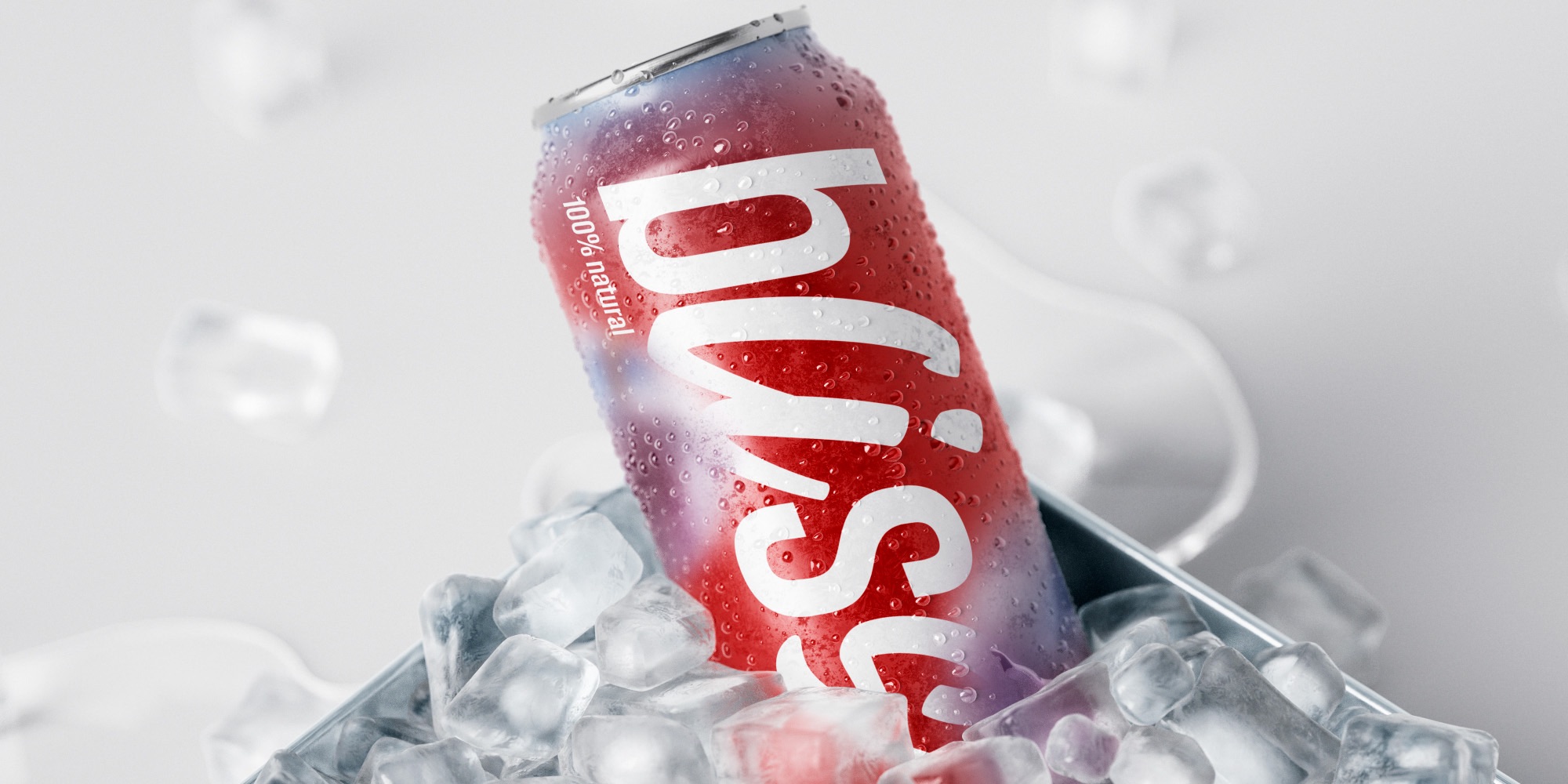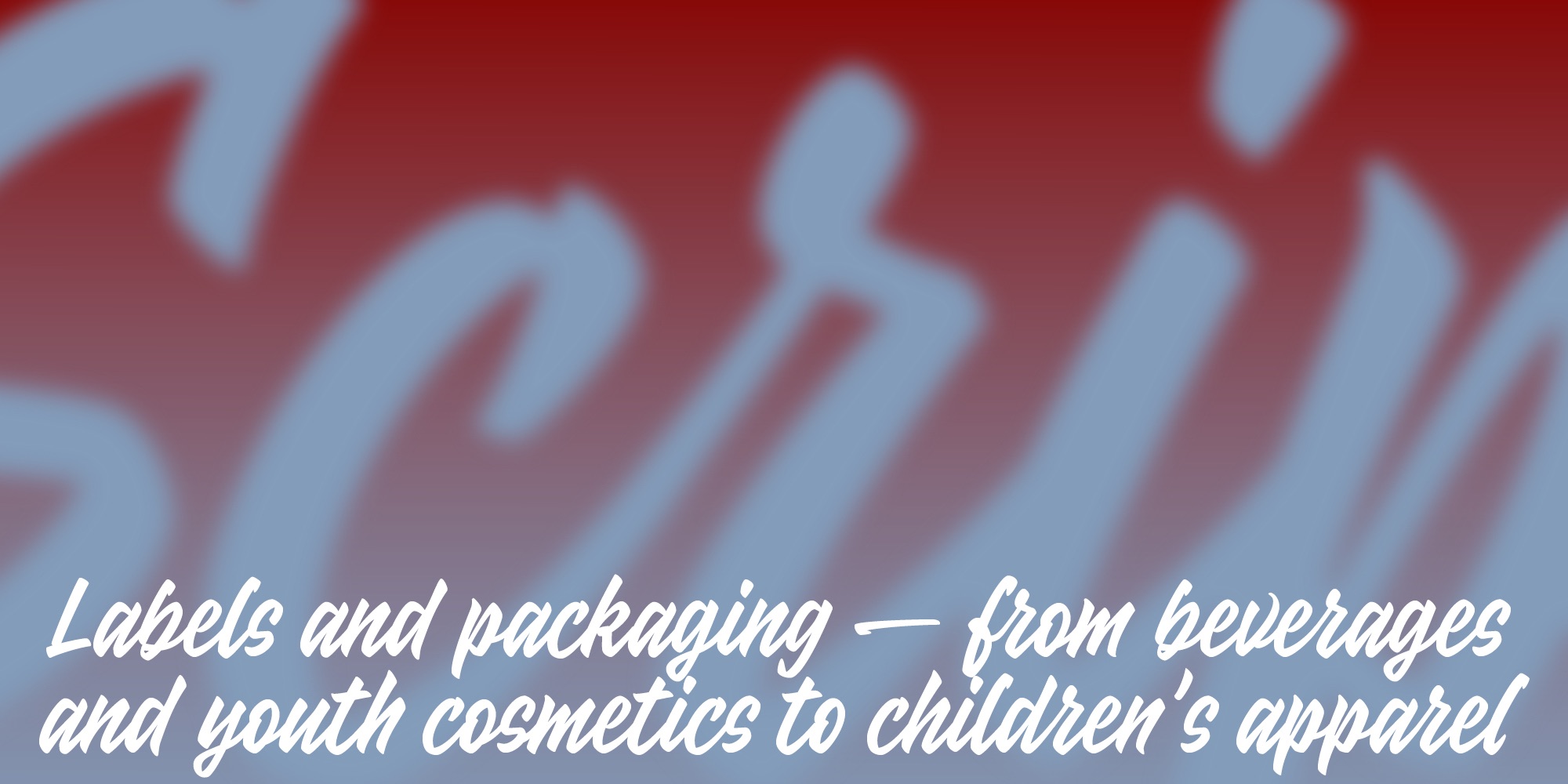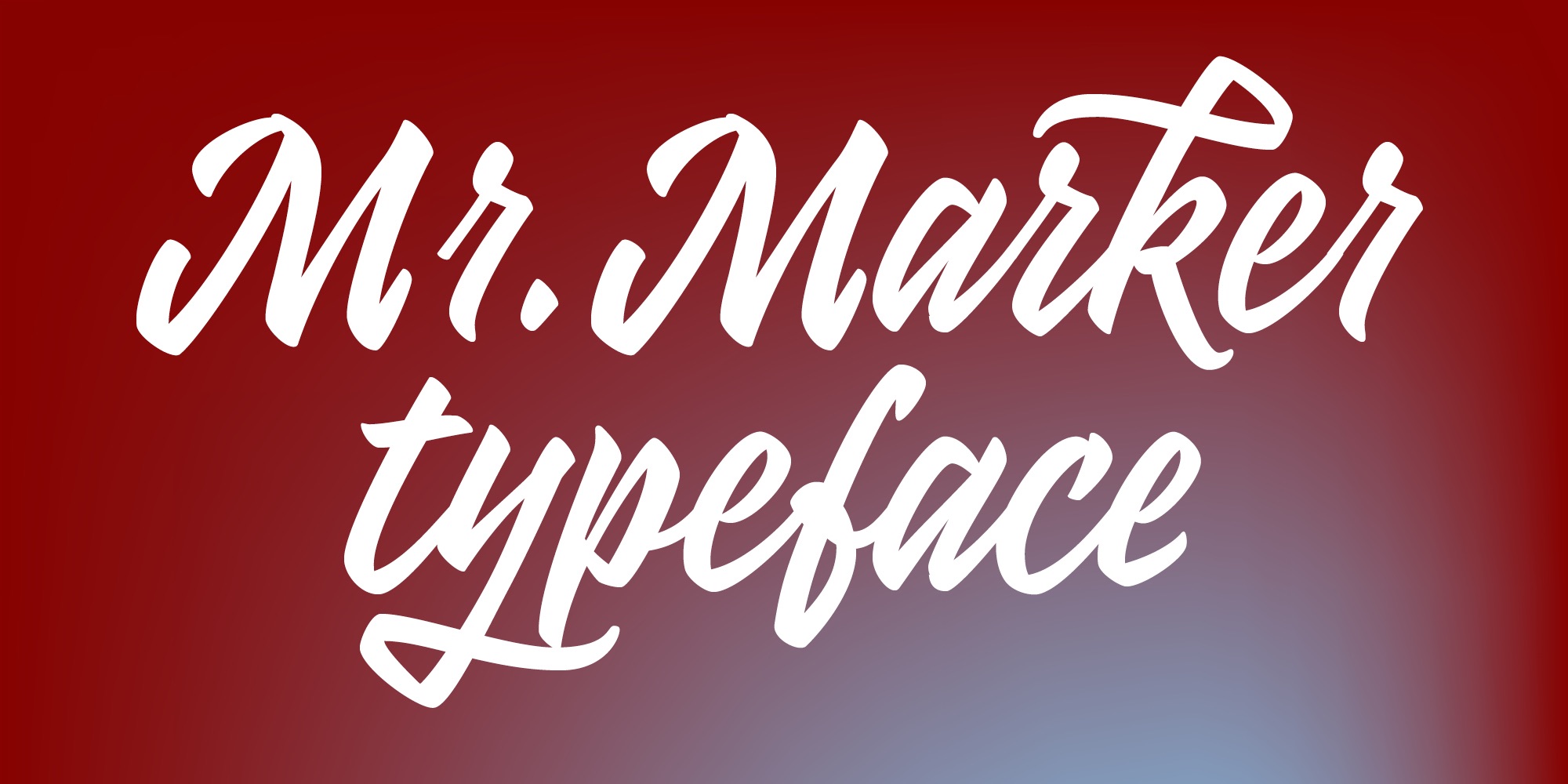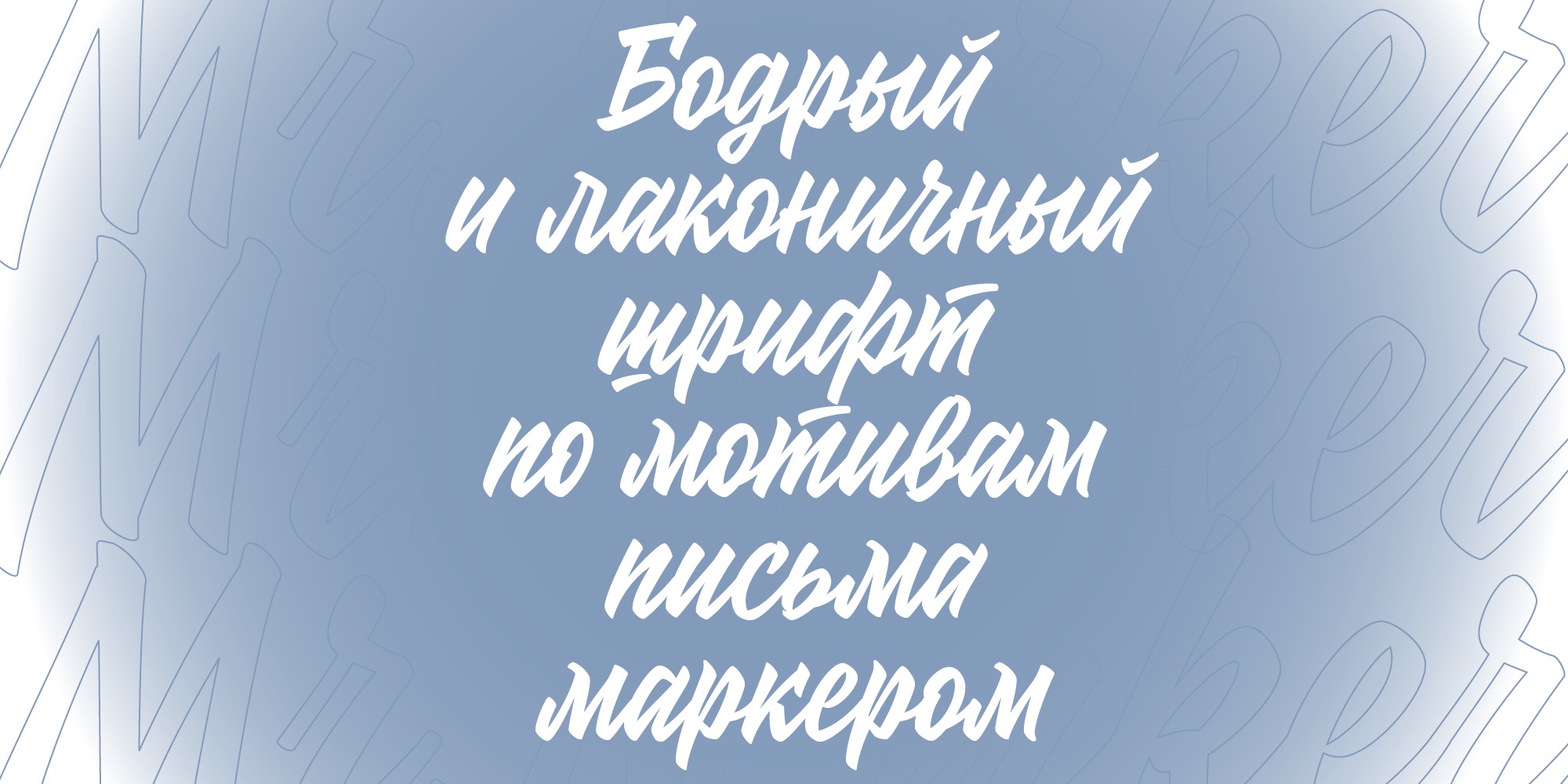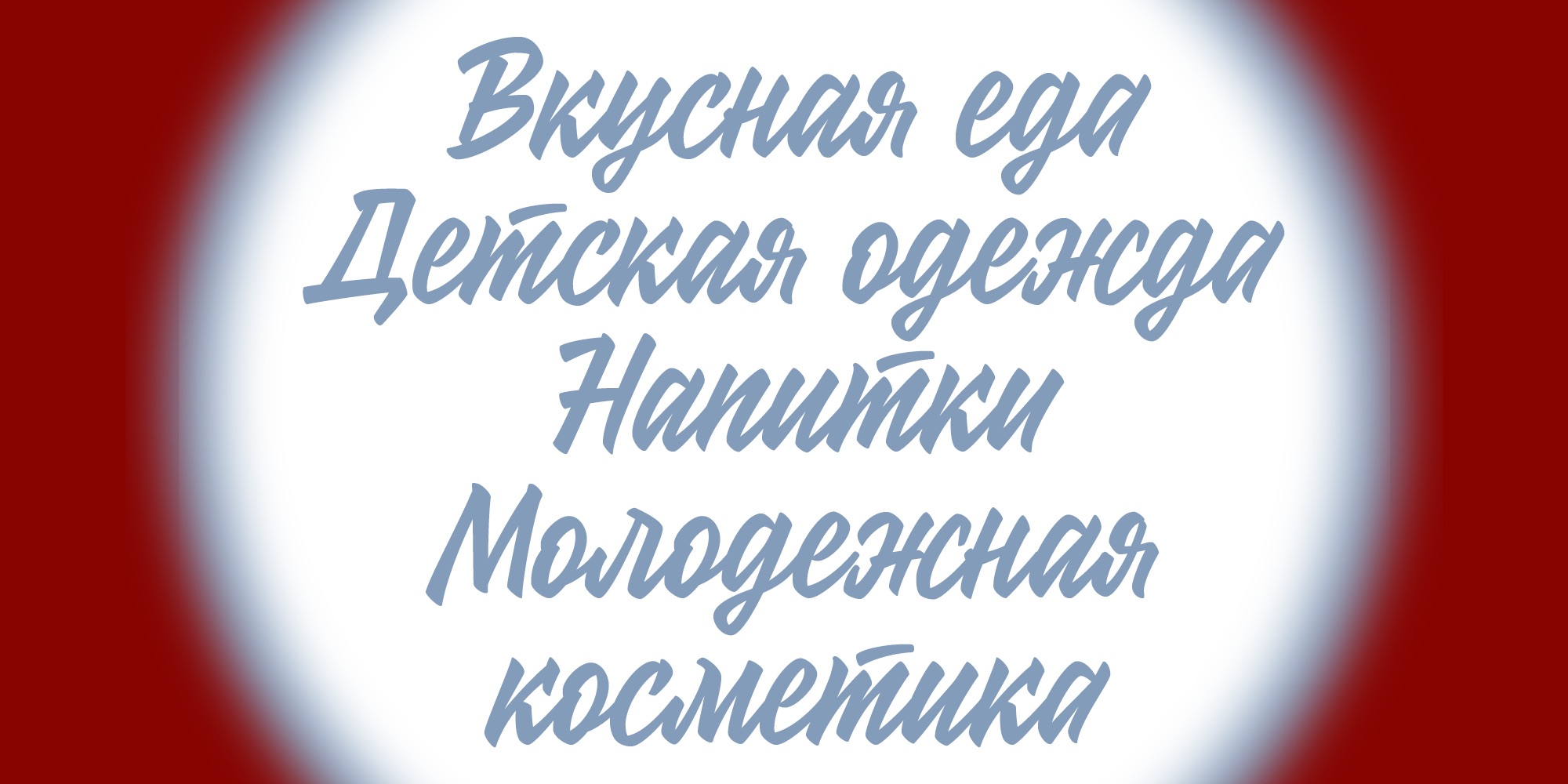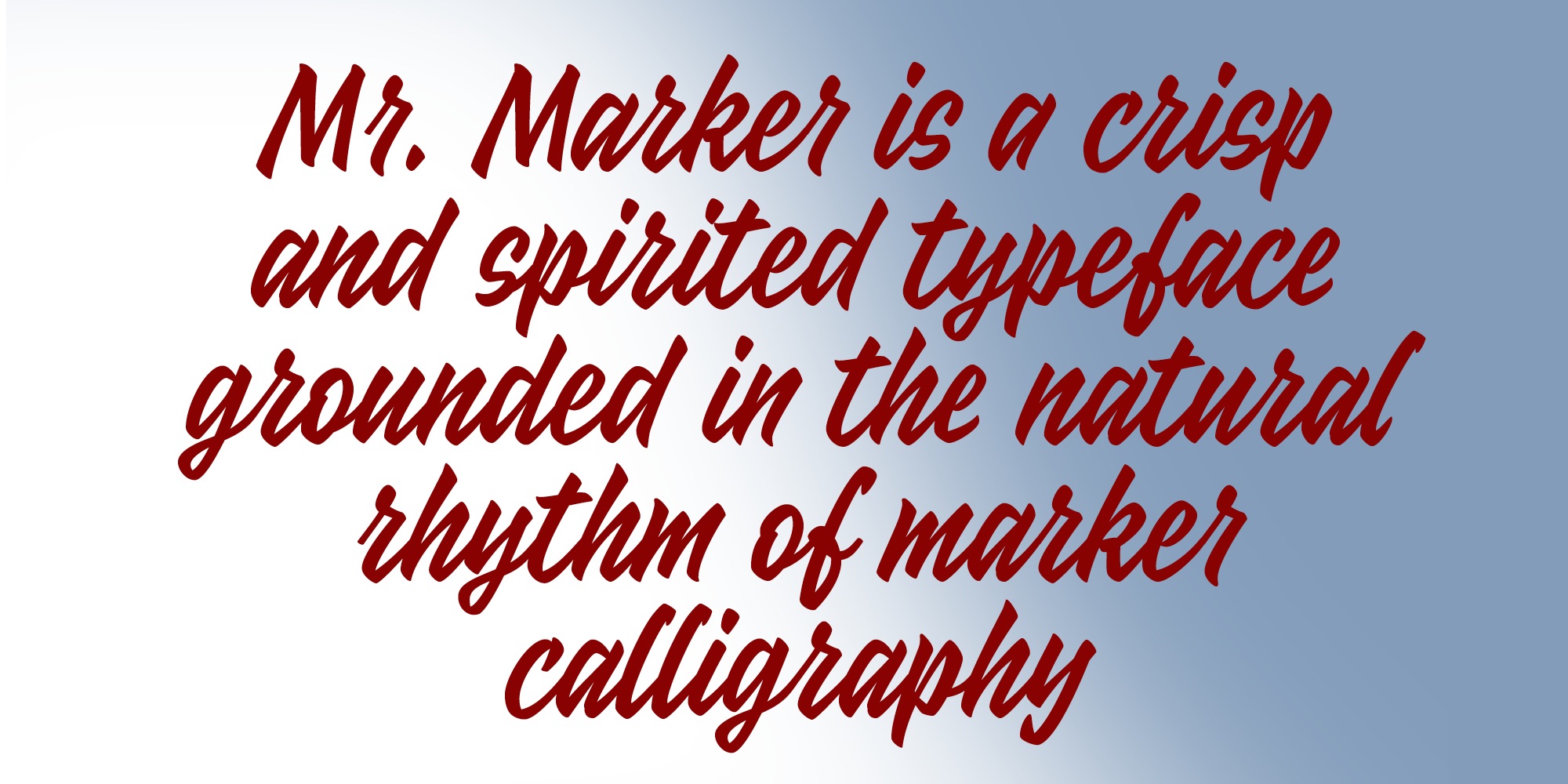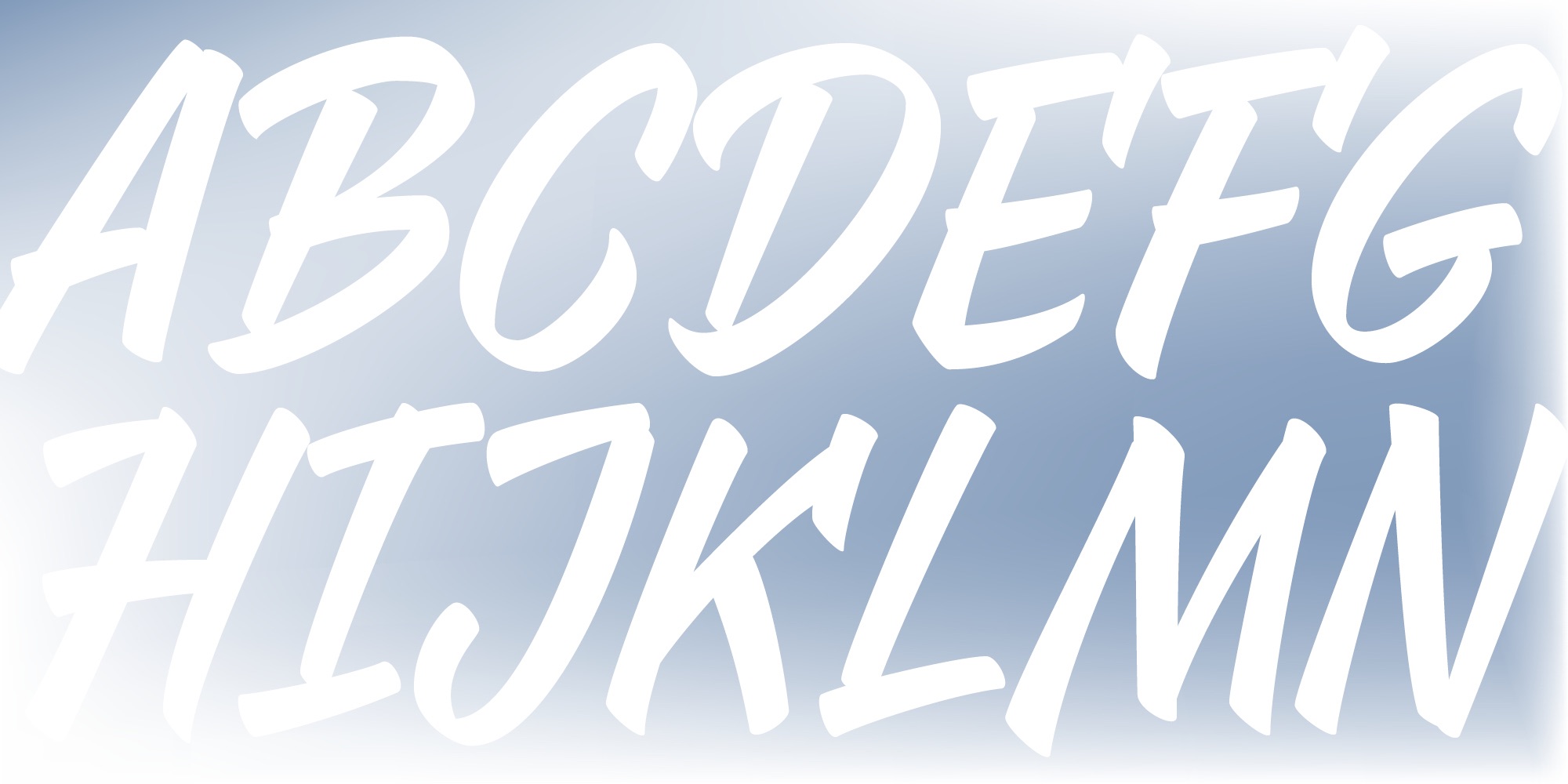
MrMarker — бодрый шрифт по мотивам письма маркером.
Он ожидаемо хорошо будет работать на этикетках и упаковке продуктов и напитков, например, крафтового лимонада, а ещё косметики. Детская одежда и добрые детские книги — Marker тоже будет кстати.
В небольших дозах скрипт будет уместен и в музыкальных проектах, и на выставках, и в более взрослых брендах.
Шрифт предназначен для работы в среднем и крупном кегле. Точный рисунок знаков и чистый контур позволяют увеличивать буквы до огромных размеров и наслаждаться их выразительностью.
MrMarker хорош как в строчном, так и в прописном наборе, так как заглавные буквы ближе по форме к печатным, чем к рукописным.
При этом в строчном наборе это связный скрипт, то есть буквы соединяются между собой, при необходимости заменяются на альтернативные формы, а для сочетаний одинаковых букв подряд в шрифте есть лигатуры.
Также в знаковый состав входят буквы с росчерками, которые при точечном использовании легко превращают слово в логотип.